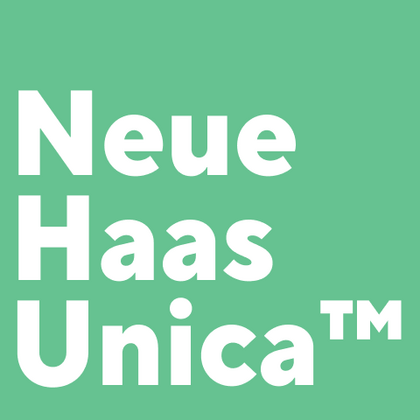
Шрифты похожие на Neue Haas Unica™
Если вы в поисках универсального гротеска с безупречной читаемостью, коллекция TypeType станет отличным решением. Это — современные шрифты, которые станут отличной альтернативой для ваших проектов. Шрифт Neue Haas Unica™ известен своей функциональностью — наши гарнитуры предлагают те же преимущества, но с важными улучшениями: для корпоративного дизайна, интерфейсов или полиграфии — наши шрифты обеспечивают профессиональное качество, современные типографические возможности и оптимизацию для цифровых экранов.
Если вы устали от «заезженных» шрифтов и ищете гарнитуры, похожие на Neue Haas Unica™, ознакомьтесь с нашими лучшими альтернативами Neue Haas Unica™. Это шрифты, которые имеют близкие характеристики, но в то же время обладают новыми уникальными особенностями дизайна. Например, относятся к той же категории шрифтов, подходят для тех же целей и имеют похожие черты, но отличаются в деталях или пропорциях.
В TypeType вы найдете передовые шрифты, такие как Neue Haas Unica™ и даже лучше: вот несколько замечательных и не столь распространенных альтернатив Neue Haas Unica™. Используйте этот список высококачественных, выглядящих как Neue Haas Unica™ шрифтов, на свой вкус. Так вы сможете подобрать еще более для вашего проекта подходящий шрифт, расширив выбор, или освежить свой дизайн. Все шрифты, представленные в этой коллекции, доступны в разных форматах и по доступным ценам, поэтому вы сможете найти тот, который соответствует любым потребностям!
Найдите отличную замену Neue Haas Unica™ и попытайтесь имитировать похожее настроение, передать нужное вам ощущение, используя его в своих проектах. Каждый шрифт, представленный на этой странице, является двойником шрифта Neue Haas Unica™, фактически его полным аналогом.
TT Chocolates — изящный гуманистический гротеск сo сбалансированными пропорциями, близкими к классическим. Шрифт с приятным дружелюбным характером, который интуитивно воспринимается как что-то знакомое.
TT Commons™ Classic — универсальный геометрический гротеск для широкого круга задач.
TT Severs — это геометрический гротеск с ярко выраженными элементами внутренних скруглений. Отличительной особенностью TT Severs является необычная форма внутренних овалов, которая отсылает нас к стилю традиционной арабской письменности.
TT Turns — геометрический гротеск с акцентными круглыми знаками и выразительными нависающими элементами. Это универсальный шрифт, который лаконично выглядит и отлично читается в маленьком размере, при этом в крупных кеглях становится акцидентным и проявляет свой характер на максимум. Он энергичный, сильный и динамичный — особенно отчётливо это проявляется в наклонных начертаниях.
TT Firs Neue — скандинавский гротеск, сочетающий выразительные графические элементы с универсальностью использования. Мы проанализировали каждый контур и графический элемент. Пересобрали шрифт заново, чтобы сохранить лучшее и исправить необходимое.
TT Interphases Pro — неогротеск, который создавался специально для работы в интерфейсах. Среди визуальных особенностей TT Interphases Pro — плавные формы скруглений, повторяющиеся во всех элементах: благодаря им большие массивы текста читаются легко и приятно.
TT Travels Text — геометрический гротеск с широкими пропорциями. Основные визуальные отличия TT Travels Text — достаточно широкие пропорции и немного сквадраченные формы овалов.
TT Norms® Pro — один из самых востребованных шрифтов студии, выбор известных мировых брендов. Более трёх переизданий за семь лет, первые строчки на MyFonts, десятки кастомизаций. Это «рабочая лошадка», которая станет незаменимой базой любой шрифтовой коллекции.
TT Commons™ Pro — один из самых востребованных шрифтов студии. Сфера его применения практически безгранична! Беспроигрышный вариант для тех, кто ищет стильный и функциональный базовый шрифт для любых проектов.
TT Hoves Pro — скандинавский гротеск с нейтральным, но в то же время узнаваемым характером. Это удобный и функциональный, при этом стильный и эстетичный инструмент для дизайнеров. Такой шрифт позволит вам решать множество разноплановых задач!
TT Supermolot Neue — непобедимое оружие в борьбе за стиль! Это технологичный модульный гротеск с футуристическим настроением и мощным функционалом. Шрифт идеально подойдёт для оформления компьютерных игр и множества других проектов.
TT Firs Neue — сбалансированный гротеск со скандинавскими мотивами. Это выразительный и привлекательный, при этом лаконичный и универсальный в использовании шрифт. Переиздан дважды, чтобы быть безупречным.
TT Rounds Neue — мягкий и дружелюбный шрифт, который умеет быть разным. В тонких начертаниях он выглядит минималистично и нейтрально. В жирных же — «надувается» и округляется, приобретая инфантильные черты.
TT Rounds Neue — гротеск со скругленными формами. В тонких начертаниях шрифт выглядит довольно минималистично и нейтрально: скругленные окончания штрихов становятся практически незаметными, на первый план выходят плавные линии.
TT Prosto Sans является шрифтовой гарнитурой на любой жизненный случай. Благодаря современным открытым гротескным формам, вы можете использовать гарнитуру почти для любой задачи.